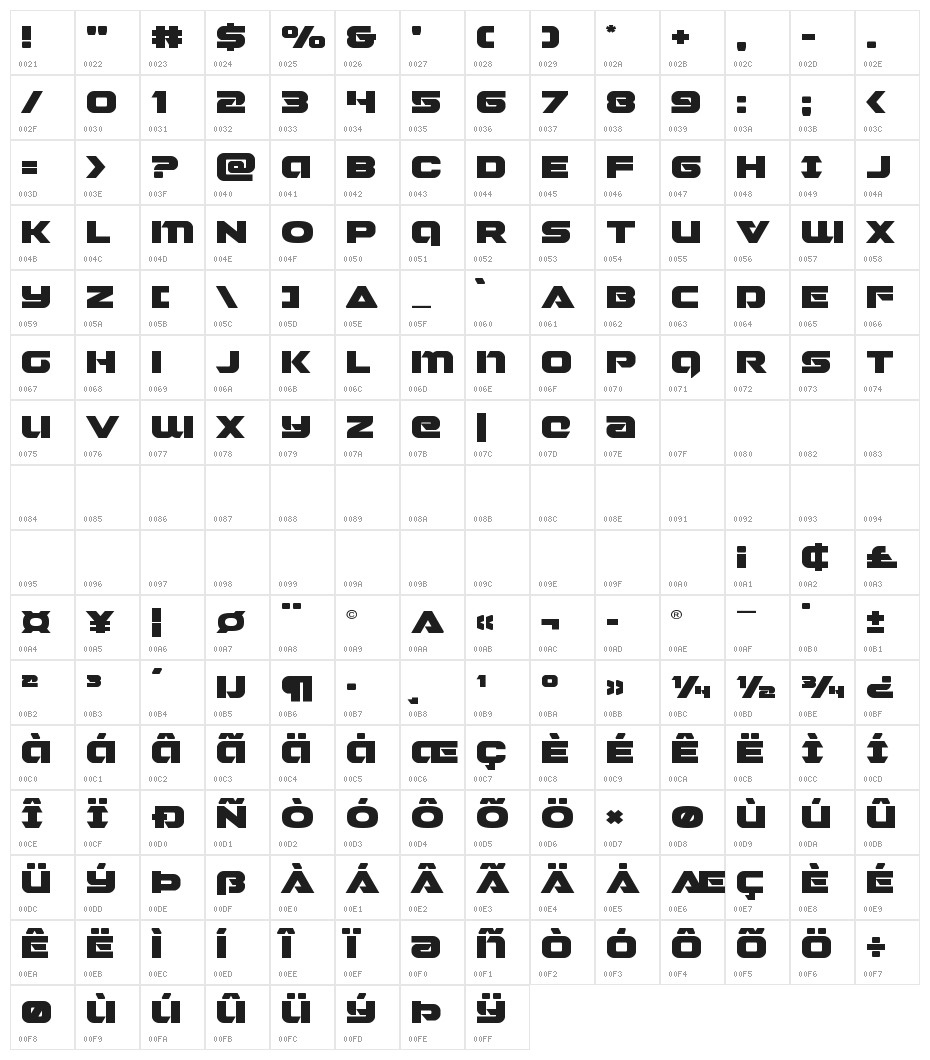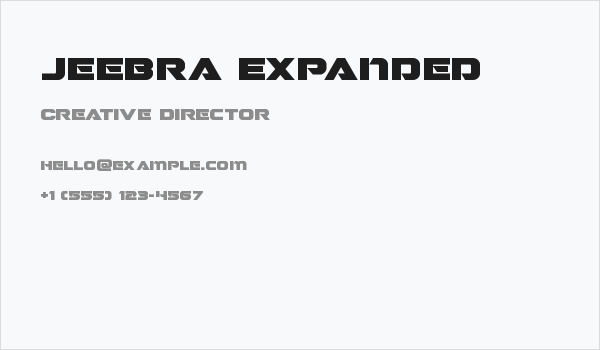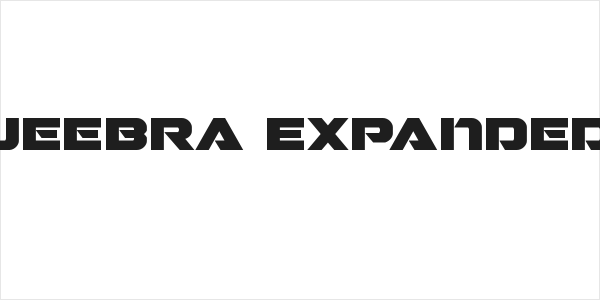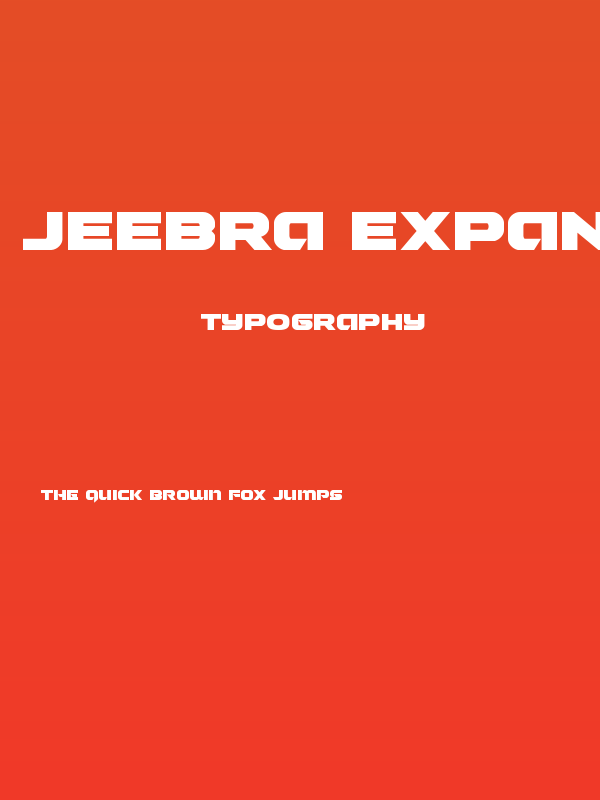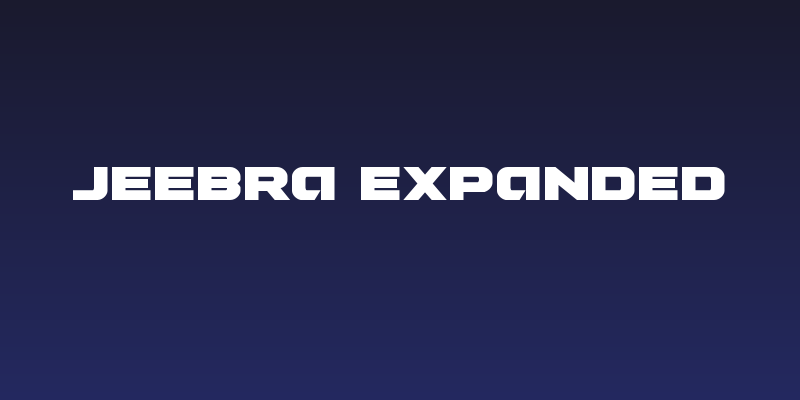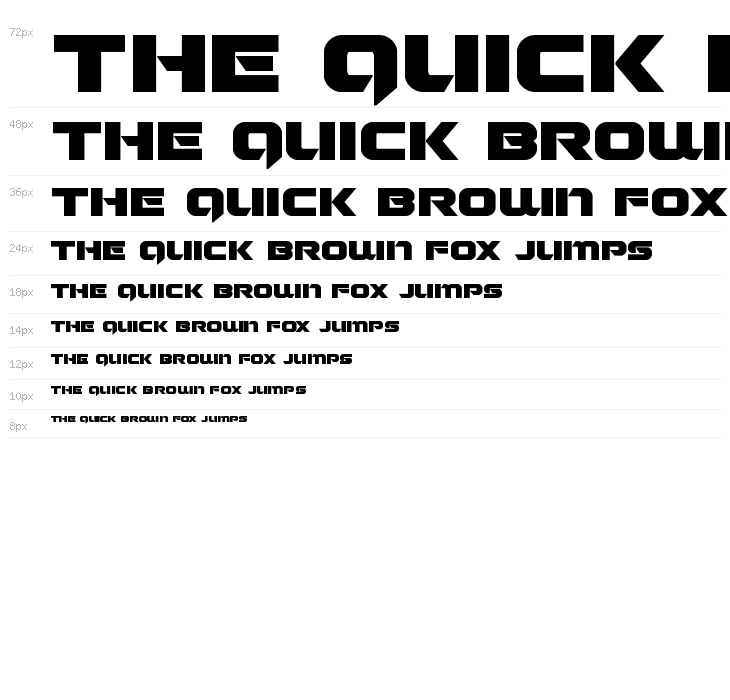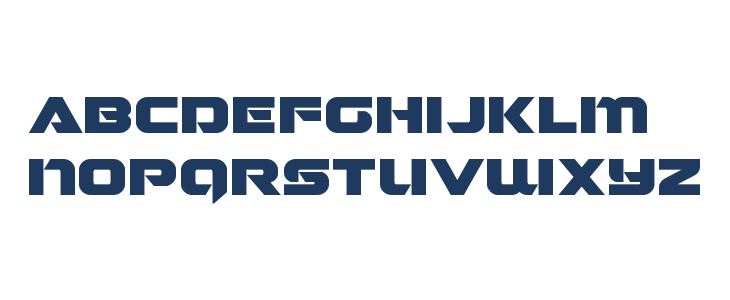
Jeebra Expanded Font
✎ Futuristic
| Vorgeschlagene Projekte | Ideal for sci-fi themed projects, technology branding, video game titles, and modern advertising campaigns. |